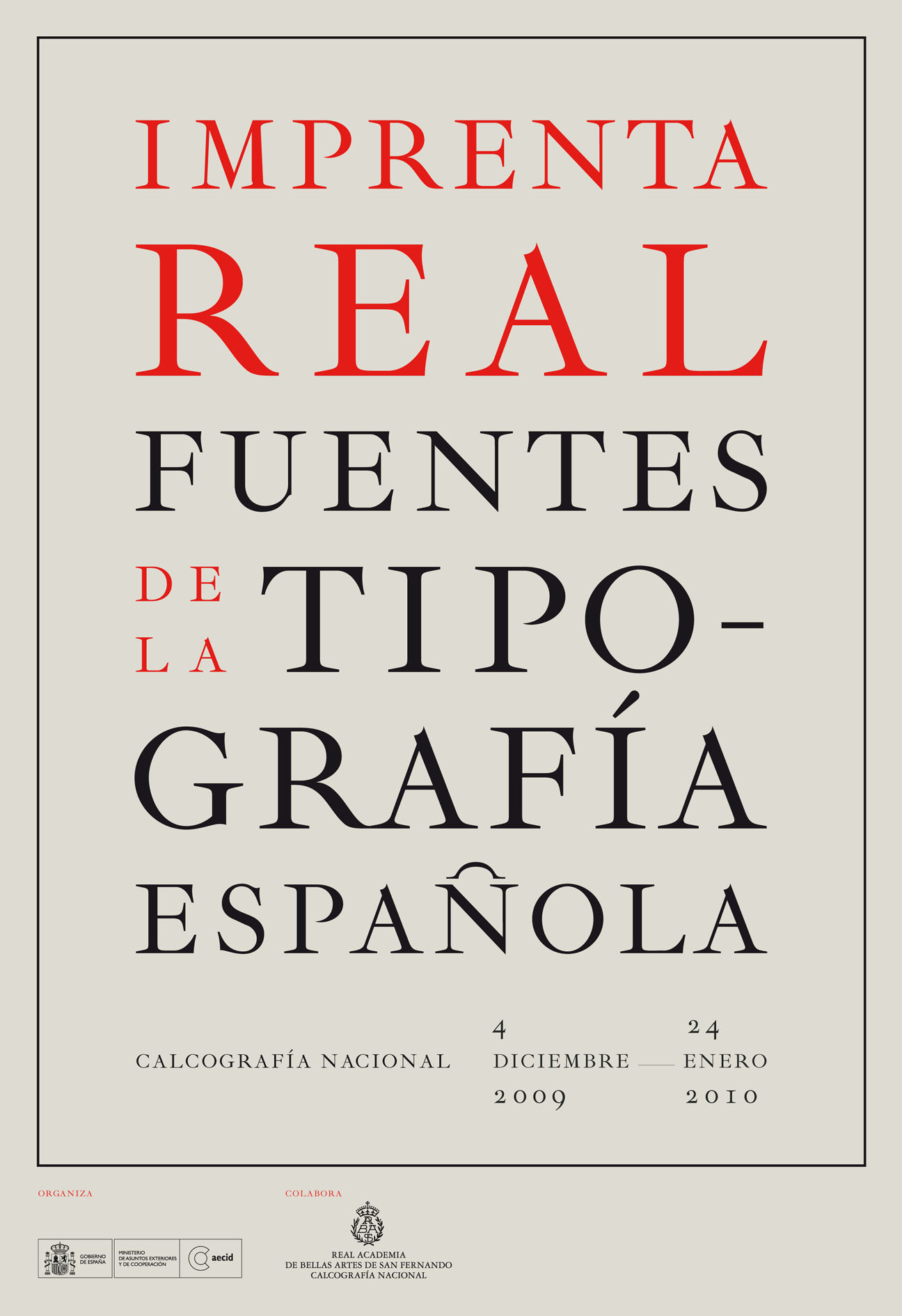
Desde el próximo 4 de diciembre hasta el 24 de enero de 2010, podrá visitarse en la madrileña Sala de Exposiciones de la Calcografía Nacional situada en la Real Academia de Bellas Artes de San Fernando en la calle de Alcalá, la importante exposición Exposición «Imprenta Real, fuentes de la tipografía española» que gira entorno al origen y evolución del diseño tipográfico en España. A continuación os dejamos con la nota de prensa correspondiente donde podreis ampliar la información sobre este importante evento.
IMPRENTA REAL. FUENTES DE LA TIPOGRAFÍA ESPAÑOLA
En los últimos años, la tipografía ha experimentado en todo el mundo un auge extraordinario de la mano del diseño y las interfaces gráficas de los ordenadores. Un nombre, ‘Ibarra Real’, sirve de muestra del trabajo que desarrollan actualmente diseñadores de la Península y Latinoamérica en el ámbito de la lengua española. Creada en el siglo XVIII y seleccionada específicamente para imprimir la que se considera mejor versión de El Quijote en castellano, hoy vuelve a estar de actualidad, más que nunca, tras años de investigación y experimentación. Nombres de lengua española buscan su sitio en el escritorio de los ordenadores de todo el mundo a través de su distribución gratuita en Internet y a través del gigante informático Microsoft, cuyos programas emplean millones de usuarios como instrumento principal de trabajo y comunicación.
La exposición ‘Imprenta Real. Fuentes de la Tipografía Española’ gira en torno al origen y evolución de nuestro diseño tipográfico. Así como la Baskerville se asocia a Inglaterra, la Bodoni a Italia o, más recientemente, la Helvética a Suiza, la cultura ‘en español’ posee unas tipografías propias y características, que han tenido su propia evolución y con las que se han impreso –o reimpreso– obras maestras de nuestra literatura a éste y al otro lado del Océano Atlántico y que, ahora, en esta muestra se reúnen, se catalogan y se analizan por primera vez.
Organizada por la Agencia Española de Cooperación Internacional para el Desarrollo, esta exposición cuenta con la colaboración de la Real Academia de Bellas Artes de San Fernando y muestra desde las herramientas que se utilizaban –los moldes y punzones–, a libros antiguos impresos con tipografías de la época, donde destacan, entre otros El Quijote de 1780, libros de Tomás de Iriarte o Ramón de la Cruz o La Conjuración de Catilina de Cayo Salustio. También nos encontraremos con fuentes digitales, libros interactivos… Su objetivo: la recuperación y revalorización del patrimonio tipográfico español.
La exposición consta de tres apartados. En primer lugar, se revisan los antecedentes caligráficos que nos llevan hasta los padres de la Ibarra Real, Jerónimo Gil y el pendolista Francisco Javier de Santiago Palomares. Estos antecedentes nos muestran la evolución de la famosa Bastarda Española, una caligrafía desarrollada a partir de otra de origen italiano. La segunda parte se centra en la edad de oro de la tipografía española. Es el reinado de Carlos III y el inicio de la Imprenta Real. El Quijote impreso por Joaquín Ibarra, con la tipografía que hoy lleva su apellido, marca el apogeo de un periodo en el que se desarrollan, por primera vez, caracteres genuinamente españoles. Nuestra época es la que cierra la muestra con las tipografías digitales actuales cuyas referencias están en la Imprenta Real. Es el trabajo de recuperación y conversión a software que están realizando diseñadores y tipógrafos basándose en los modelos históricos.
SOBRE EL COMISARIO
Con motivo del IV Centenario de El Quijote en el año 2005, el Ministerio de Industria apoya un proyecto de la Calcografía Nacional que tiene por objeto la puesta en valor del patrimonio tipográfico español procedente del obrador de la Imprenta Real. José María Ribagorda Paniagua (Madrid, 1959) fue el director de la iniciativa y recupera la tipografía de Jerónimo Gil fundida para la Imprenta Real y utilizada para la realización de El Quijote de 1780 impreso por Joaquín Ibarra.
Ribagorda es profesor de Diseño en la Universidad Complutense de Madrid y Jefe del Departamento de Estudios Superiores de Diseño de la Escuela de Arte Diez de la misma ciudad. Creador del estudio Arquetipo, ha diseñado tipografías como la Hispana (1996) o Cromotex (2003). Además, ha sido miembro fundador del I Congreso de Tipografía en España. ‘La exposición conecta el diseño con la cultura y la tecnología a través de la puesta en valor del patrimonio histórico, la búsqueda de la identidad formal de la lengua a través de su escritura y mediante la investigación y el desarrollo de software de fuentes para ordenador. El hilo argumental es la Imprenta Real, su aportación en el pasado y su futura aportación en el mundo del diseño. Son pocas las ocasiones en las que encontramos reunidas joyas de procedencia tan distinta. Con esta muestra, se ofrece un punto de vista nuevo sobre la forma de la lengua castellana’, explica el comisario.
SOBRE EL CATÁLOGO
Casi 350 páginas con el objetivo de convertirse en libro de referencia en el diseño tipográfico español.
Está estructurado en dos vertientes, una actual desde el punto de vista del diseño y una histórica que explica los procesos de elaboración de la tipografía española. Esto lo convertirá en una fuente de consulta imprescindible para diseñadores e historiadores porque es una suma entre el valor de la historia de la tipografía española y el valor presente y futuro del diseño. Para Ribagorda, ‘el diseño es más que moda y tendencia, también es un patrimonio cultural influido por la tecnología. Hoy se ha popularizado, antes pertenecía a un mundo muy cerrado, pero en la actualidad es mucha la gente que tiene algún conocimiento sobre esta disciplina. Lo mismo sucede con las tipografías, hay un amplio sector de personas –de todos los ámbitos–, que conocen las tipografías, que las emplean a diario… Es por eso, que éste es un buen momento para poner en valor las tipografías españolas. La exposición y el catálogo comparten un tema fundamental: el diseño de letras’, aclara.
Este catálogo cuenta con la colaboración de diseñadores como Alberto Corazón, Rubén Fontana o Andreu Balius, entre otros, e historiadores como Elvira Villena, Albert Corbeto o Gabriel Sánchez. Los colaboradores, procedentes de ambos lados del Océano, nos explican los contenidos de la exposición desde la experiencia del diseño, pero también nos hablan de los procesos históricos y del sentido de la muestra.
CAMINO DE CHILE
Madrid es una primera parada para esta exposición que tiene su próxima cita en Chile en marzo de 2010, coincidiendo con el V Congreso de la Lengua Española. AECID cumple así con unos de sus fines, la continua promoción de la cultura española en el exterior. Un viaje que ha marcado e inspirado el montaje de la exposición. Los manuscritos, libros y herramientas se alojan en vitrinas-caja que se convierten en su propio embalaje (y protección) para viajar. Como ejemplo, el embalaje contenedor de libros se reutiliza como banco durante la muestra. Vitrinas-caja móviles y modulares que se mueven libremente por un tapiz tipográfico de retícula cuadrada, que les permite adaptarse a cualquier espacio. Cada vitrina-caja se ha construido como una metáfora de la geoda de una amatista, ruda en su exterior y delicada en su interior. Una base funcional formada por el embalaje –a modo de pata– y una caja de cuidados materiales y acabados que tendrán el objeto expuesto.